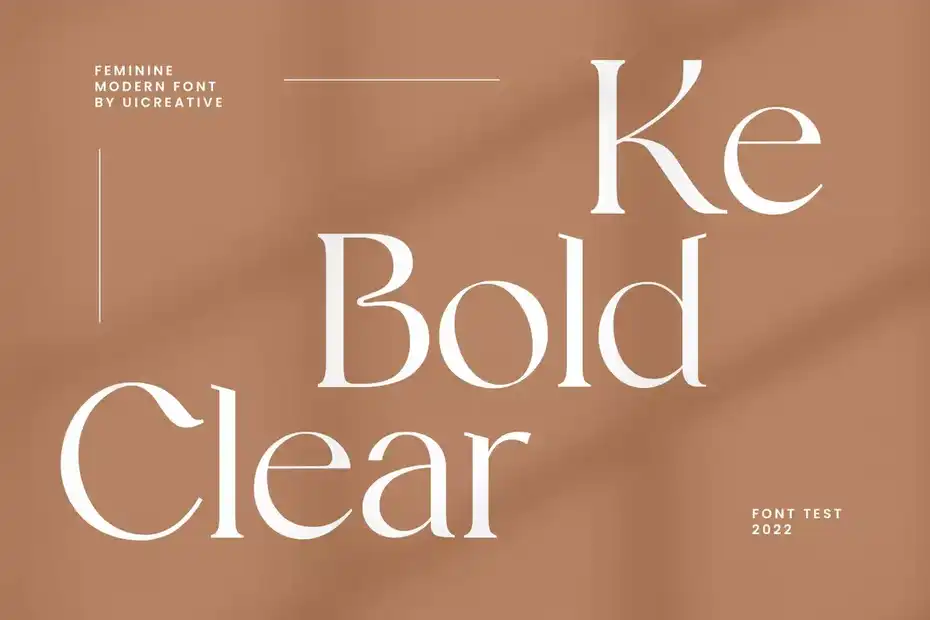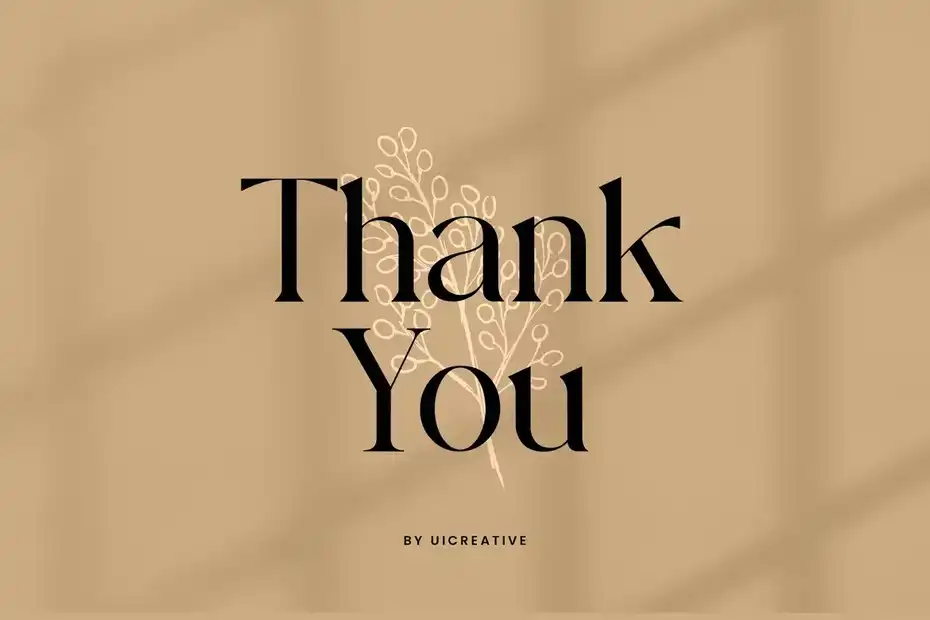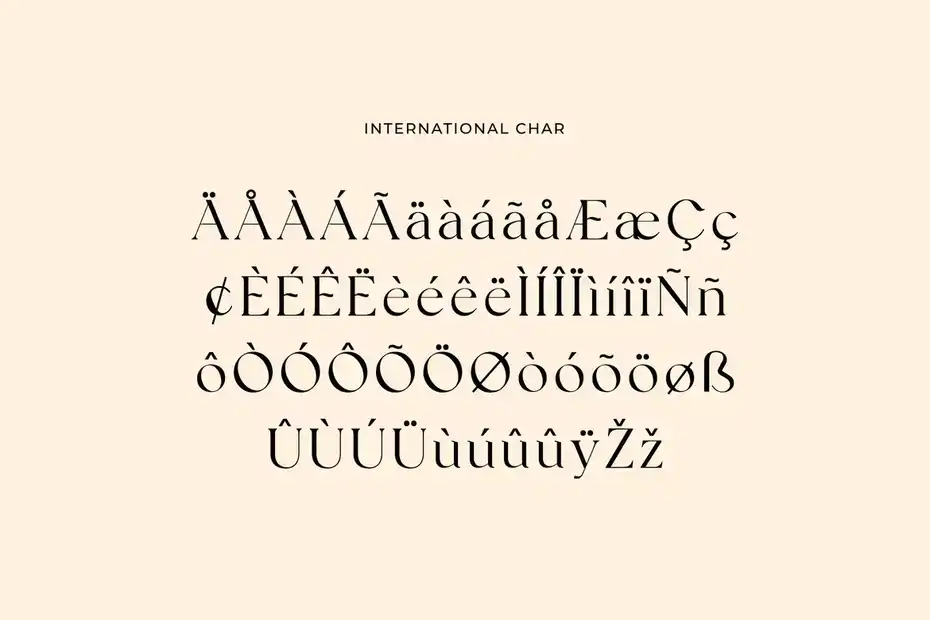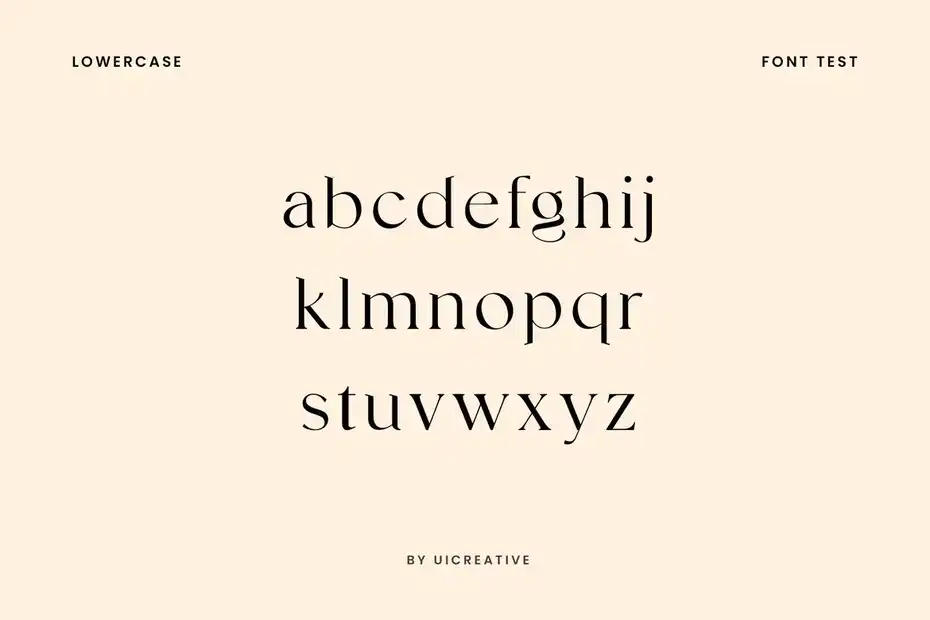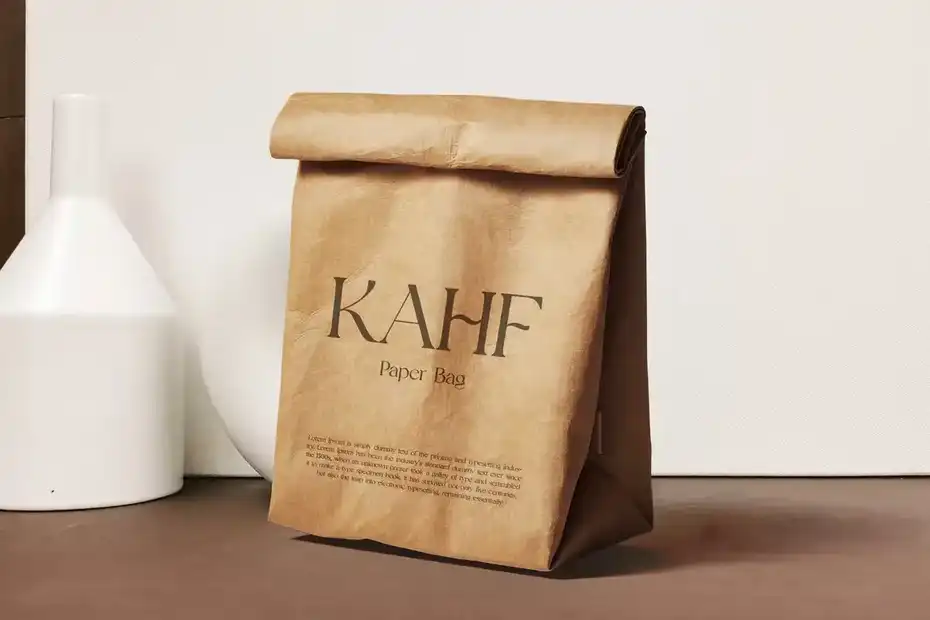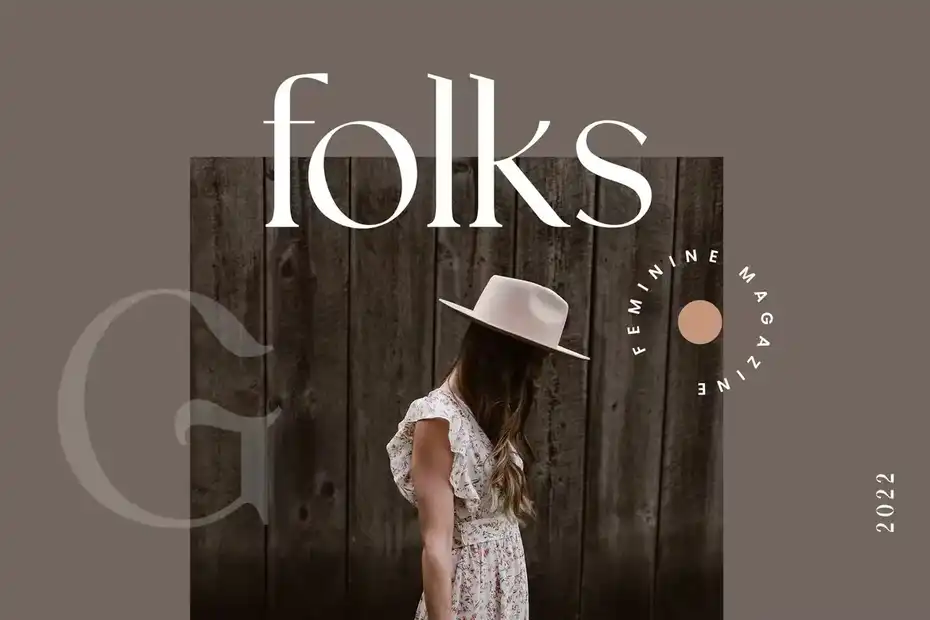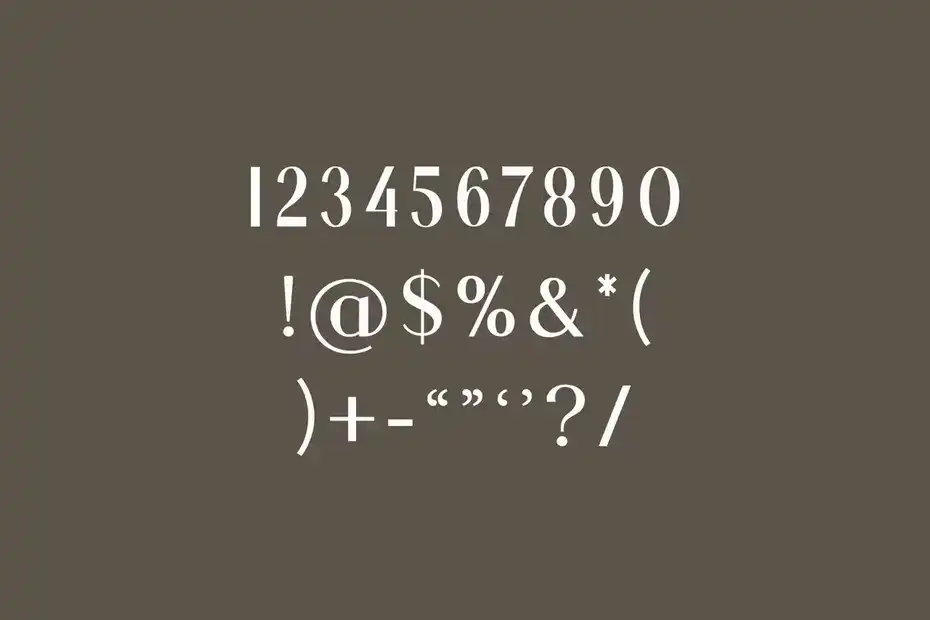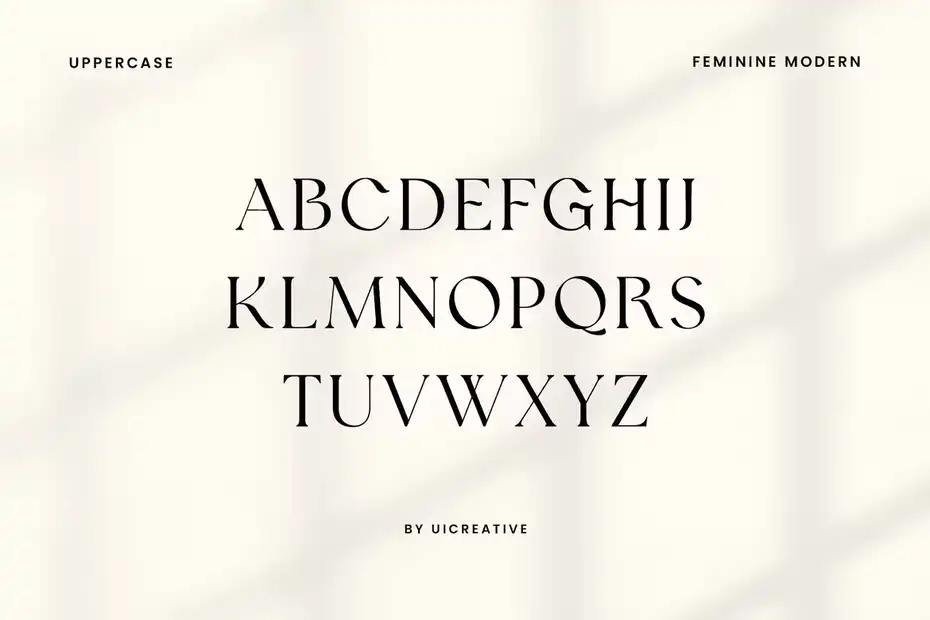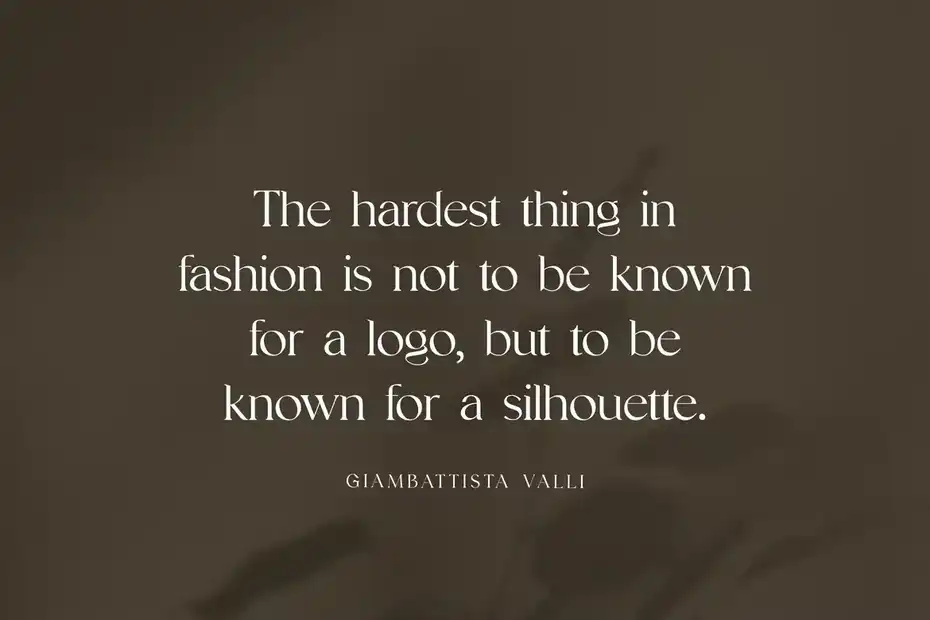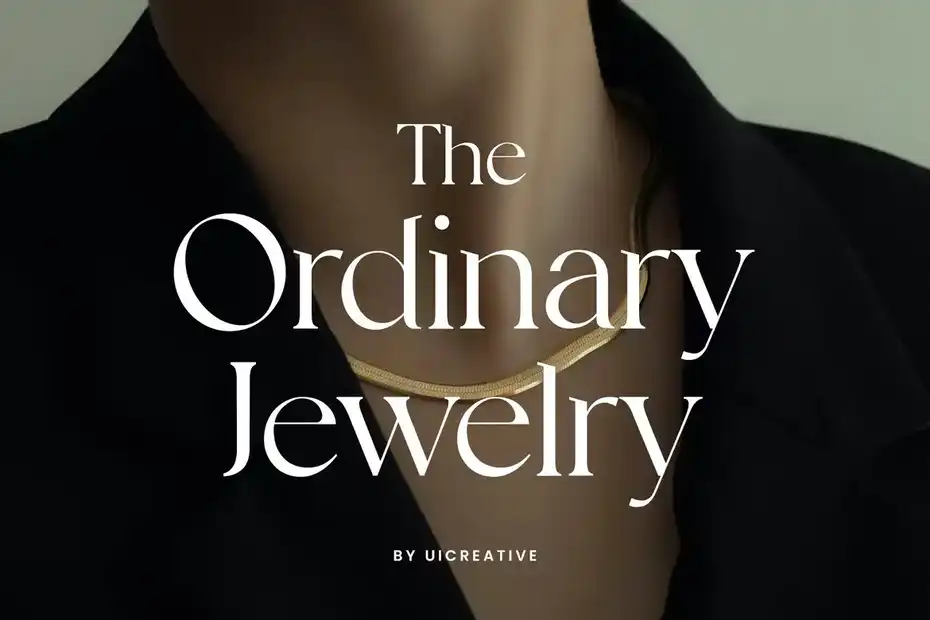
دانلود فونت انگلیسی Silvania Modern Serif Font
فونت انگلیسی Silvania Modern Serif Font : این فونت یک فونت مدرن Serif است که برای پروژه های مختلف مانند: امضا، برندینگ، لوگو، عروسی، نقل قول تایپوگرافی، جلد مجلات یا کتاب، سربرگ وب سایت، لباس، طراحی بسته بندی و غیره مناسب میباشد.
• سبک: Serif